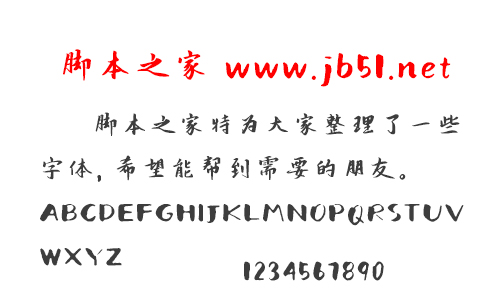
蘭米靜心粗行楷字體是蘭米字庫推出的一款手寫藝術(shù)粗行楷字體,字形優(yōu)美,整體看上去美觀大方,適應(yīng)于報紙和雜志和書籍中常用字體, 海報、個性促進(jìn)品牌標(biāo)志設(shè)計、字體設(shè)計等領(lǐng)域,歡迎喜歡蘭米靜心粗行楷字體的朋友前來下載使用。